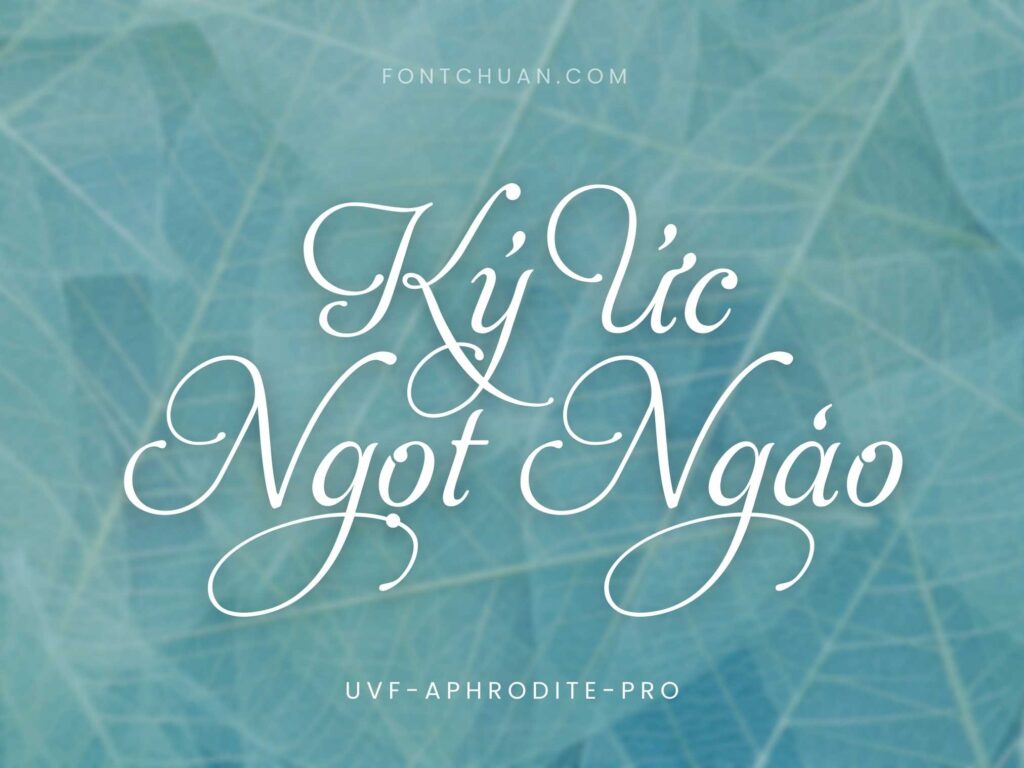
Font UVF Aphrodite Pro Việt Hóa
UVF Aphrodite Pro là một phông chữ thư pháp thanh lịch, được thiết kế bởi Maximiliano R. Sproviero và Sabrina M. Lopez. Với các đường nét mềm mại và uyển chuyển, phông chữ này mang lại cảm giác tinh tế và lãng mạn, đồng thời có thể được sử dụng như một Font chữ ký, lý tưởng cho các thiết kế logo cá nhân, thiệp cưới hoặc các dự án cần dấu ấn riêng biệt và tinh tế. Phông chữ này đã được sưu tầm và đăng bởi thành viên của Font Chuẩn, đáp ứng nhu cầu đa dạng trong cộng đồng thiết kế.